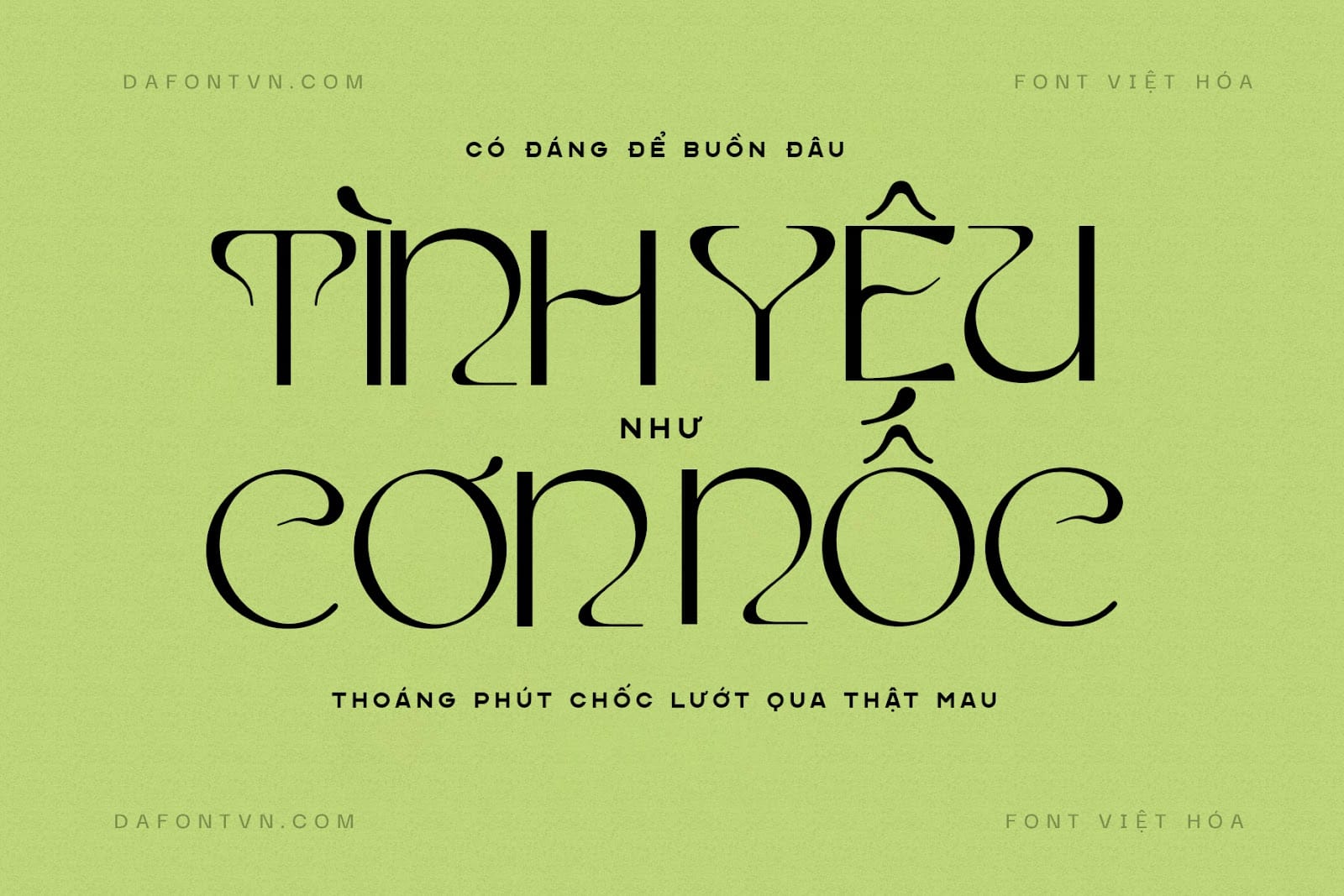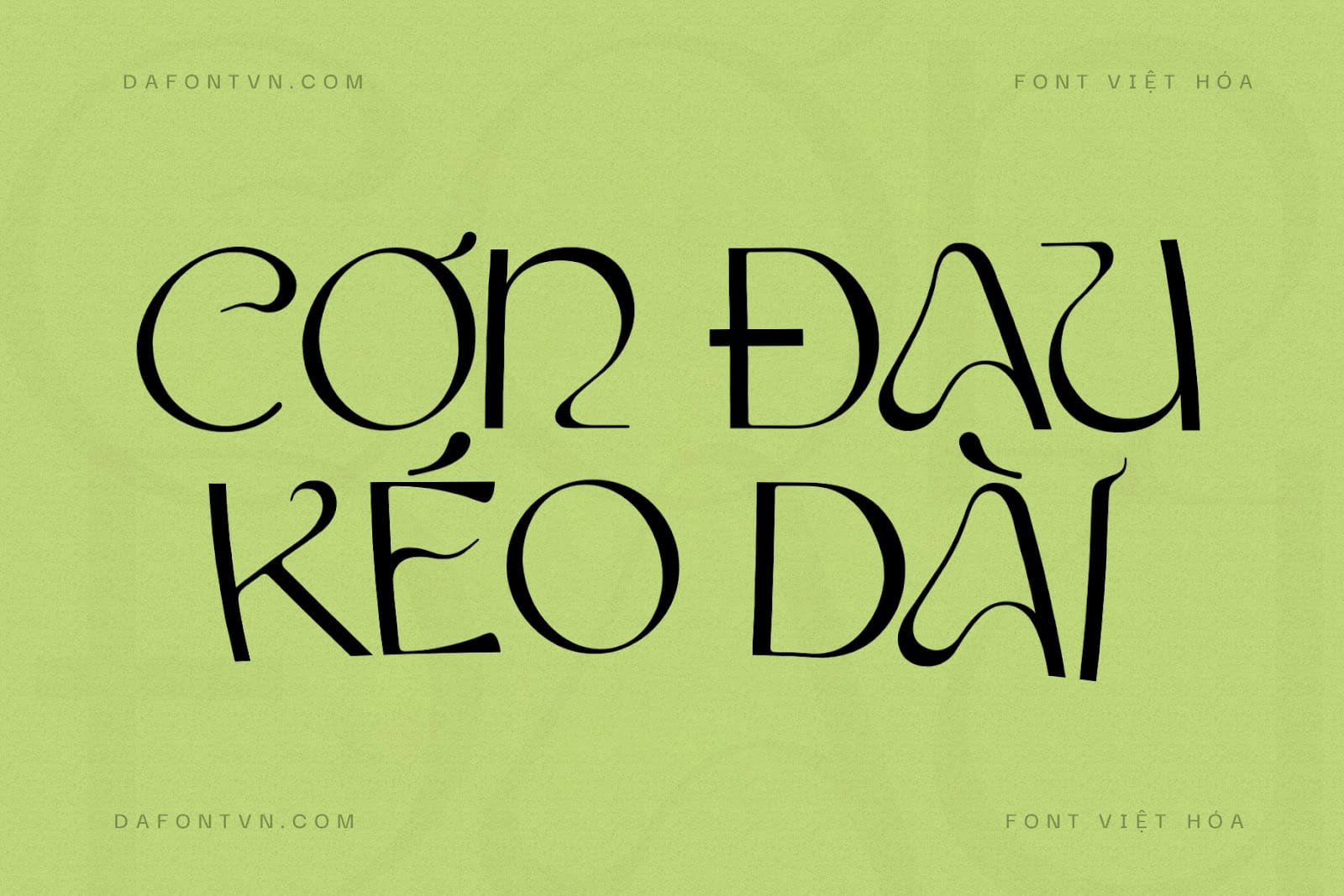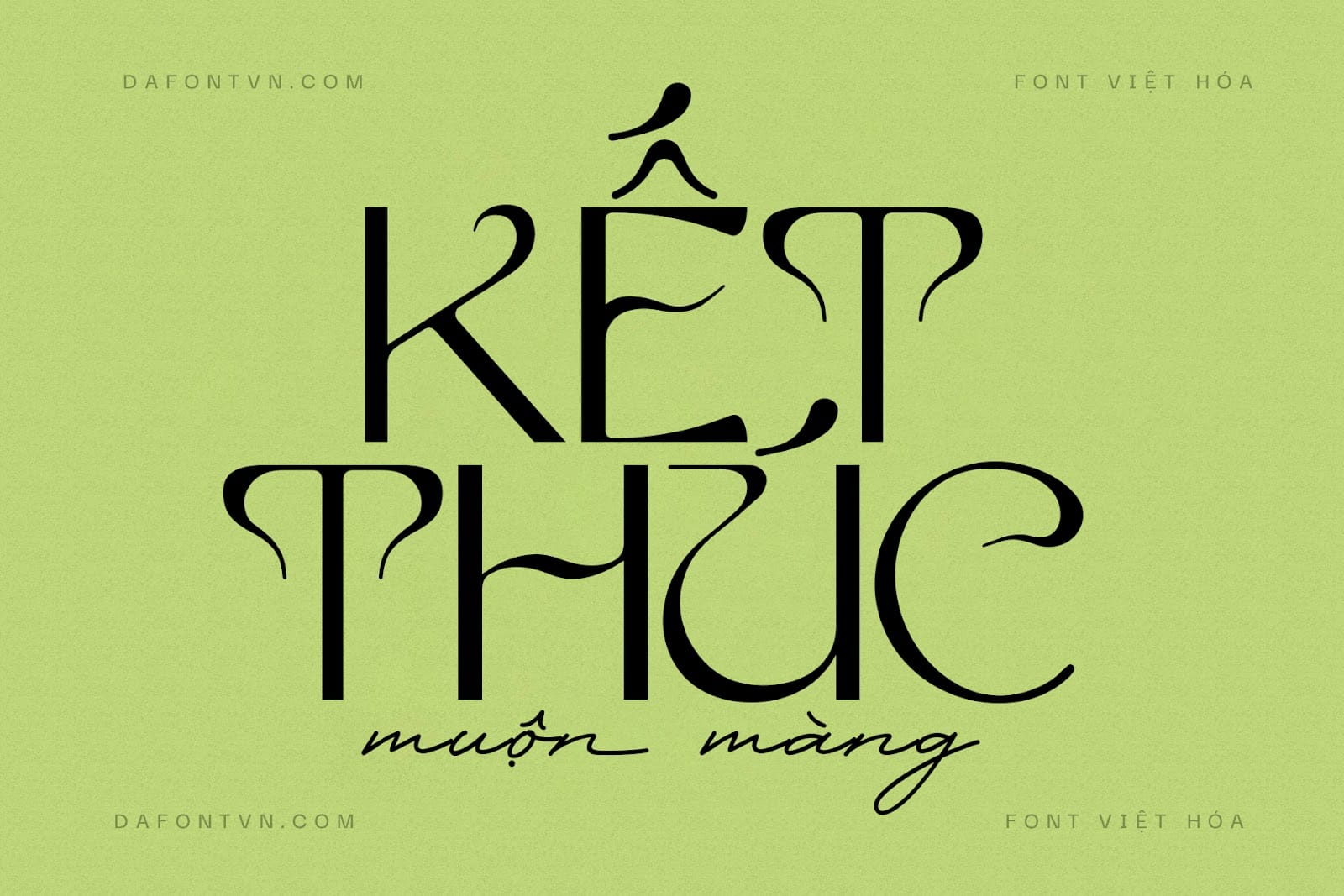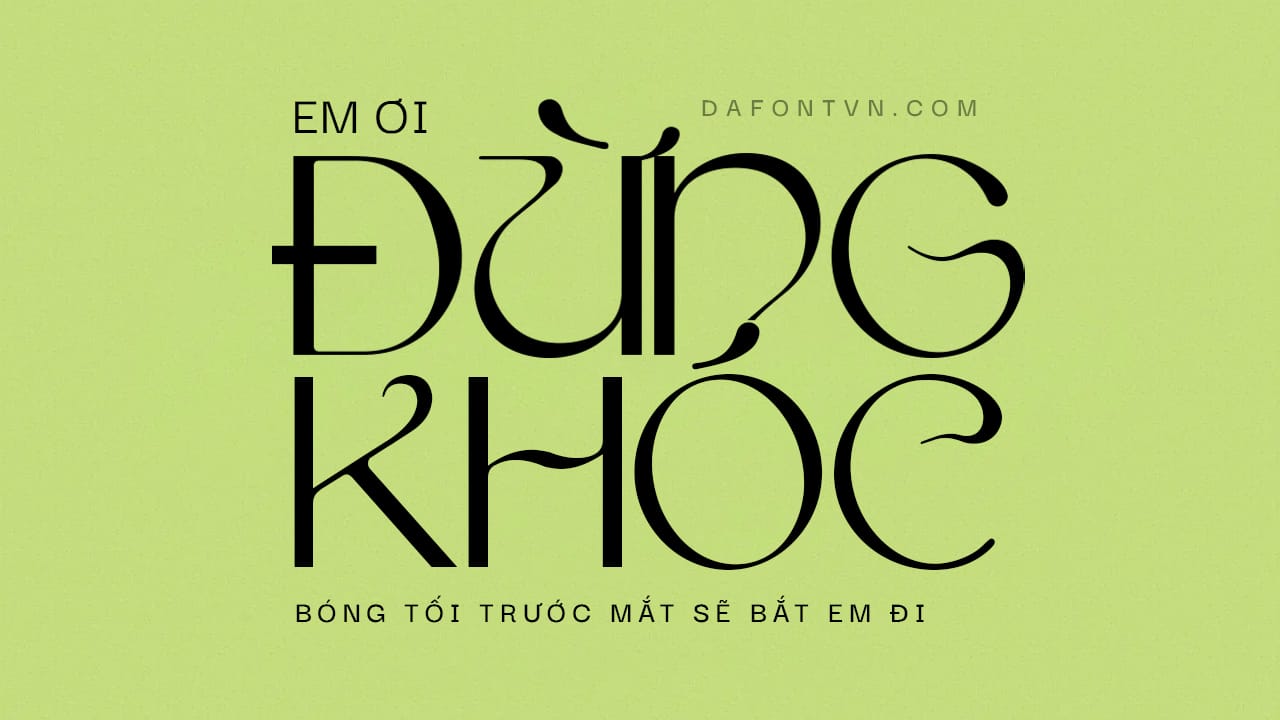
Tenebras Font Việt Hóa – 1 kiểu font chữ hiển thị đẹp mắt Tenebras là kiểu chữ in hoa sans serif lấy cảm hứng từ art nouveau và Edda, kiểu chữ từ năm 1900 do Heinrich Heinz Heune thiết kế.
Font Tenebras mang một hơi hướng cổ điển và hiện đại với các đường cong mềm mại và ấn tượng vì vậy phù hợp cho nhiều thiết kế khác nhau như thiết kế poster, typography, bìa sách, logo, banner, quảng cáo… Nếu bạn đang tìm kiếm 1 font chữ hiển thị độc đáo và lạ mắt thì Tenebras rất phù hợp dành cho bạn.
Font Tenebras được việt hóa đầy đủ, kerning, chỉnh sửa và tối ưu. Ngoài ra font đã được chỉnh sửa lại hoàn chỉnh hơn so với font gốc, để bạn có thể gõ ở cả chữ thường và in hoa, cũng như mã hóa PUA.